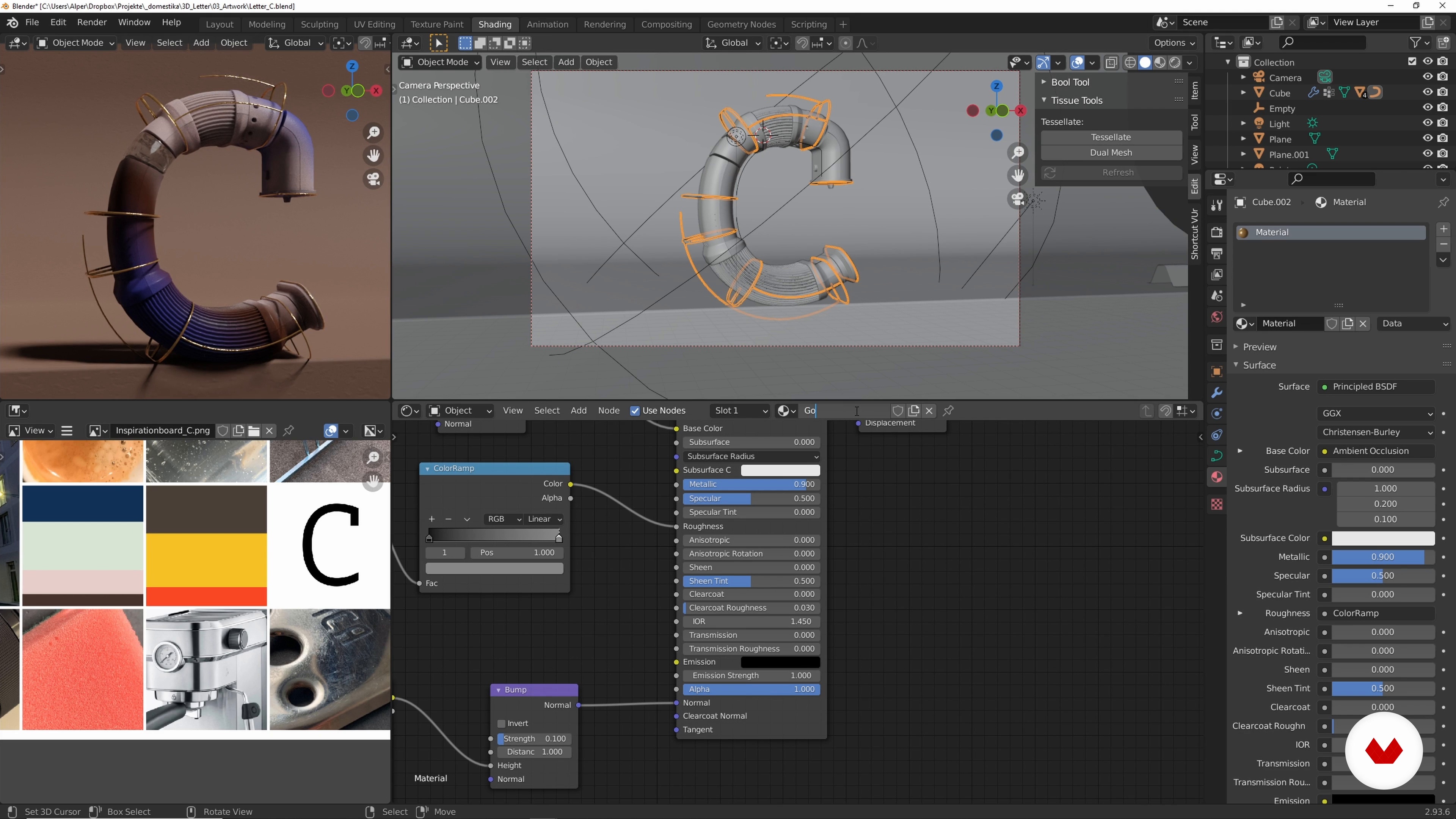
Typografia 3D w programie Blender
Więcej shaderów i sceny
O lekcji wideo: Więcej shaderów i sceny
Podsumowanie
“Następnie pokażę Ci inne materiały, które możesz zastosować do swoich listów i na scenę, takie jak Glass i Gold Shader.”
Na tej lekcji wideo Alper Dostal porusza temat: Więcej shaderów i sceny, która stanowi część kursu na platformie Domestika: Typografia 3D w programie Blender. Naucz się różnych technik trójwymiarowego modelowania liter w programie Blender i baw się surrealistycznymi efektami poprzez łączenie kolorów, materii i tekstur.
“Więcej shaderów i sceny Na koniec stworzyliśmy nasze pierwsze materiały a w następnej lekcji stworzymy więcej shaderów, aby nieco urozmaicić list. Kontynuujemy z cieniowaniem ze szkła akrylowego do naszego zbiornika na wodę a także zadbaj o bąbelki. Wybierzmy go w panelu Materiał Czy możemy już to wyjąć? lub utwórz nowy. Wyjmiemy to na razie i zrobimy nowy, przejdź do Nowego. Tutaj potrzebujemy transmisji. Oznacza to, że zmieniamy to na 100, musimy zmniejszyć szorstkość i już widać, że całość wygląda jak szkło. Oto całość znowu z Ctrl + B, dzięki czemu zaoszczędzimy na renderowaniu. to jest...”
Podsumowanie kursu: Typografia 3D w programie Blender